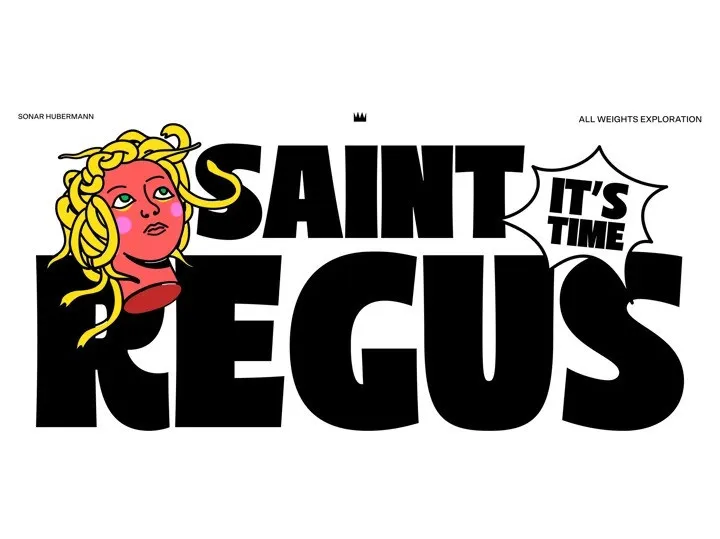
Este é um tipo de fãntese sans serif criado pela Sonar Hubermann com um estilo aprimorado para a indústria, cheio de personalidade forte e vital. É uma fonte que está sempre se desenvolvendo, inspirada por suas características agressivas e cativantes. A família totaliza 8148 caracteres, incluindo gírias padrão e contexto multilíngue, o que oferece inúmeras possibilidades para projetos de design, tanto digitais quanto impressos. A desenvolvedora do SaintRegus está empenhada em explorar a influência dessa fonte por meio de sua forma de exibição proporcional. Com uma riqueza de oportunidades e aplicação variada, esta fãntese sans serif é perfeita para designers que buscam adicionar um toque forte e distintivo aos seus projetos.